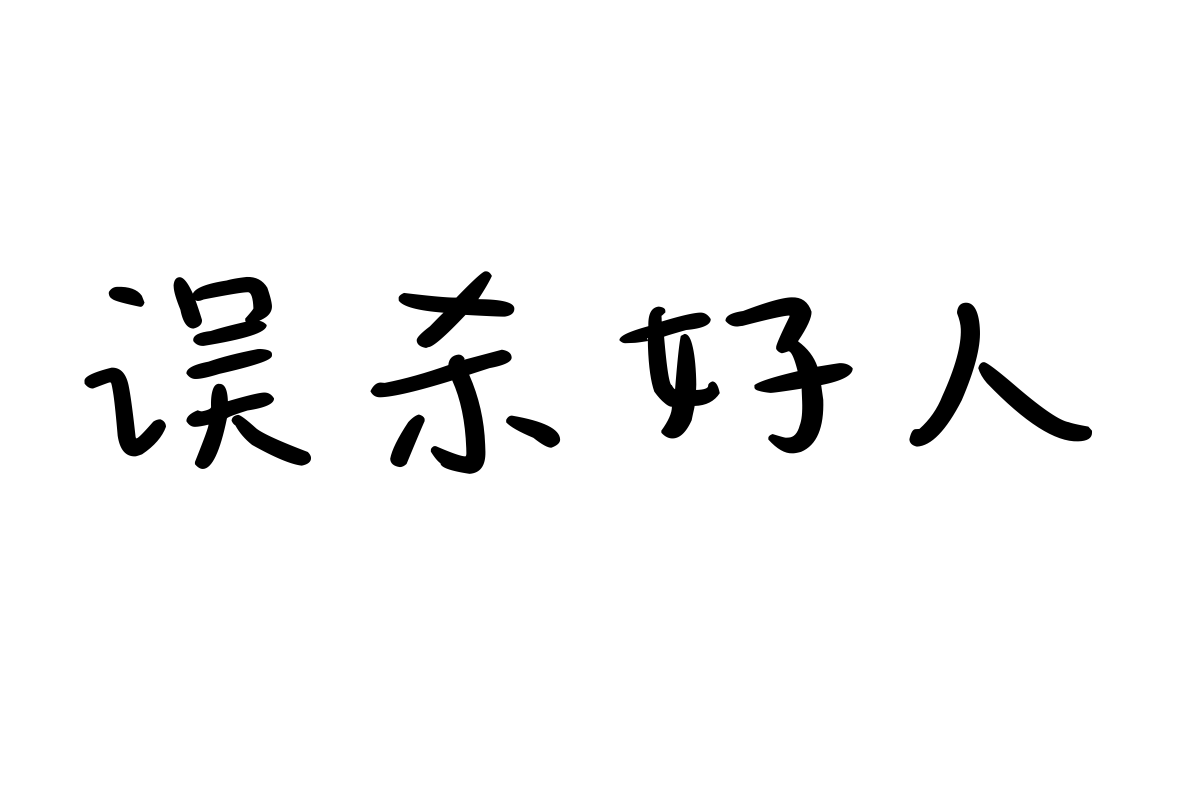
汉仪新蒂珍珠奶茶是一款现代感强烈的字体,具有以下特点:
1. 字形结构:该字体采用了简洁的线条设计,使得整个字体看起来更加干净、利落。字母之间没有多余的装饰,给人一种简约而时尚的感觉。
2. 笔画粗细:在保持整体线条流畅的同时,每个字母的笔画粗细都有所不同,增加了字体的层次感和立体感。这种设计使得字体更加生动有趣,能够吸引人们的注意力。
3. 字间距:该字体的字间距适中,既不过于拥挤也不过于稀疏,使得整个字体看起来更加协调、平衡。同时,适当的字间距也有助于提高阅读舒适度。
4. 风格特点:汉仪新蒂珍珠奶茶字体具有现代感和时尚感,适合用于各种商业宣传、广告设计等场合。同时,由于其简洁明了的特点,也适合用于儿童读物、教育类材料等需要注重易读性的场合。
总之,汉仪新蒂珍珠奶茶是一款具有现代感和时尚感的字体,适合用于各种商业宣传、广告设计等场合。同时,由于其简洁明了的特点,也适合用于儿童读物、教育类材料等需要注重易读性的场合。